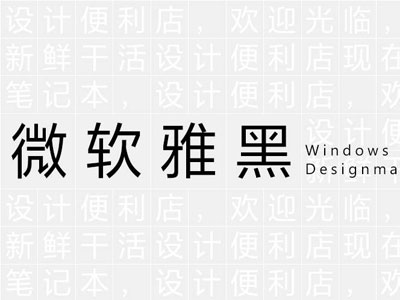
【微软雅黑更新】
在微软雅黑被开发出来的多年后,微软听取了来自中国会员的反馈意见,上周四终于在Win 10 build 17025预览版中更新了微软雅黑字体,以提高可读性、对称性和外观。显著的改动包括:
01.额外的字重
增加了三个额外的字重:Semlight、Semibold和Heavy,默认情况下额外字重将预装在中文系统下,非中文系统也可以单独下载。
02.字形调整
微软团队优化了Hinting引擎,增加了间距,字型比旧版的要更加瘦长,弱化笔画转折,提高了笔画收尾处的的斜度,中宫负形的调整,让字体更有呼吸的空间,笔画更加细长精致。
03.添加字符集
微软雅黑添加了199个字符从而完整支持了国家语言委员会制定的标准《通用规范汉字表》。
04.重新设计的标点符号
标点符号一直是最为诟病的一点,而今,微软重新设计了字体中所有的标点符号和符号。
【微软雅黑就是兰亭黑】
为什么明明是两个字体却是同一个授权呢?因为最开始,两款字体设计是基于同一个设计原型,微软委托方正为其设计字体之时,方正将最初的字形授权给微软,微软为了让字体在屏幕上更加清晰易读,请美国MonoType公司在字库中加了精细指令,并将完成的字体取名为微软雅黑。
而方正在原型的基础上做了更多风格完全不同的优化,并推出了比微软雅黑更漂亮的兰亭黑!并将微软雅黑也集合进来,将它们并称为方正兰亭黑。